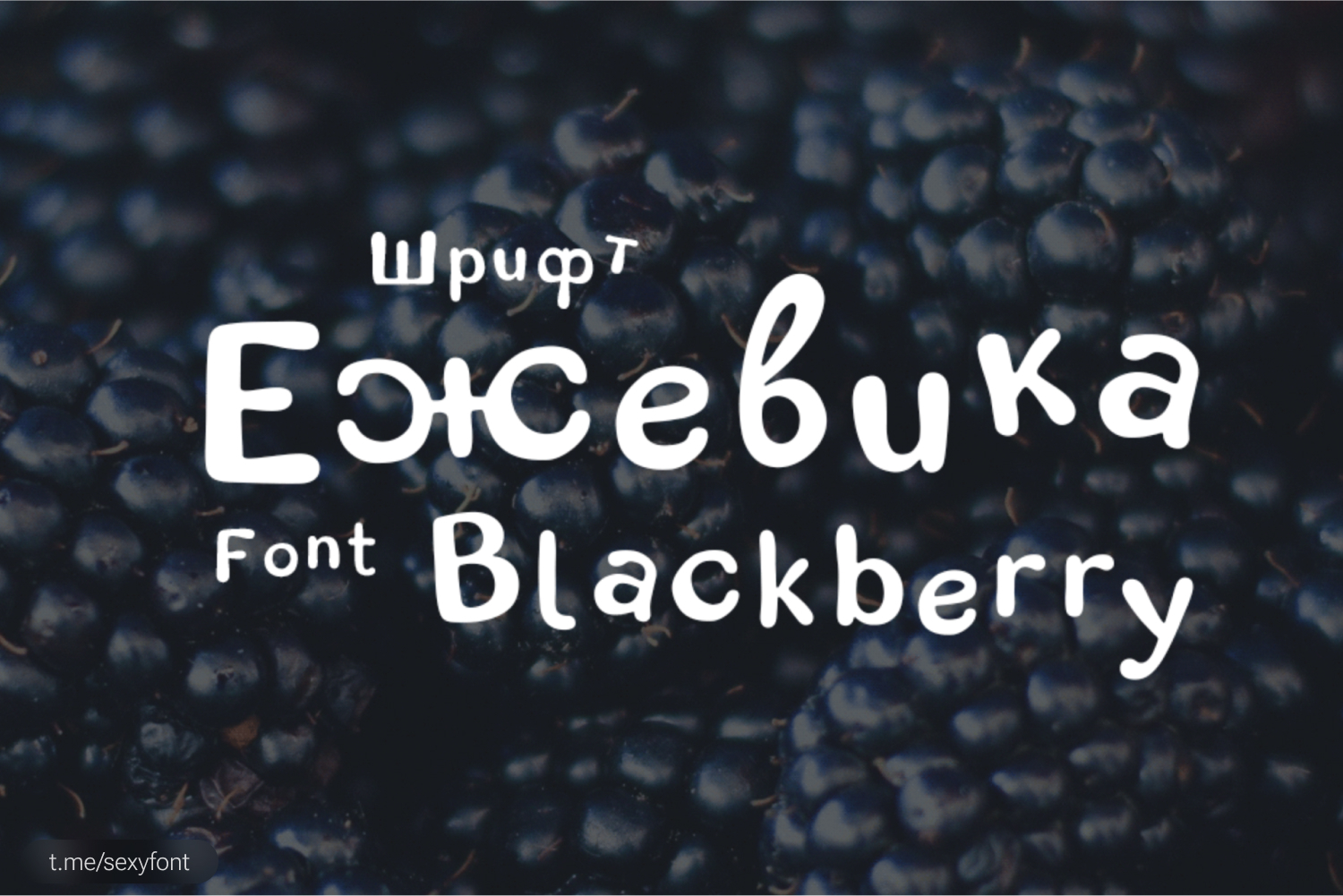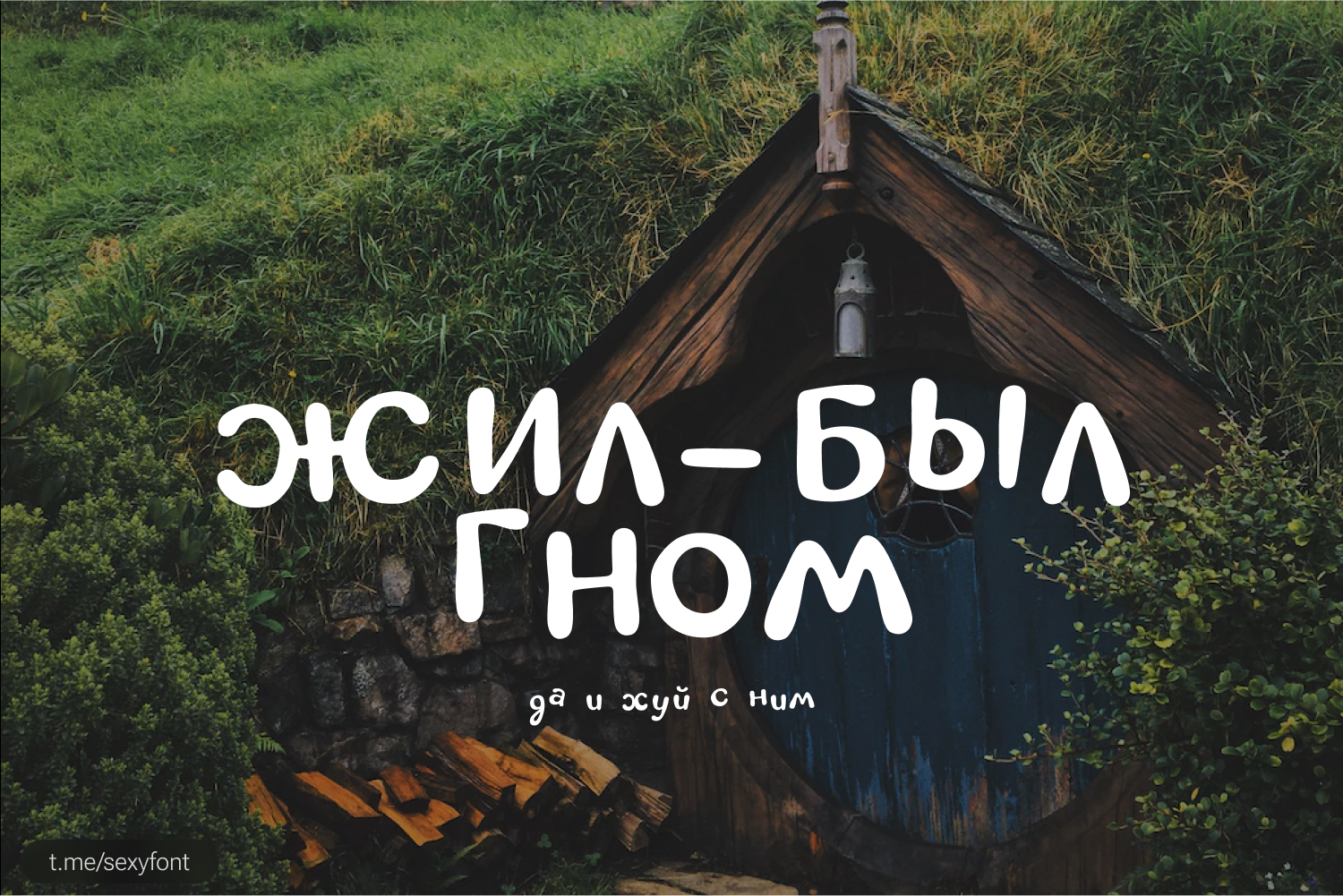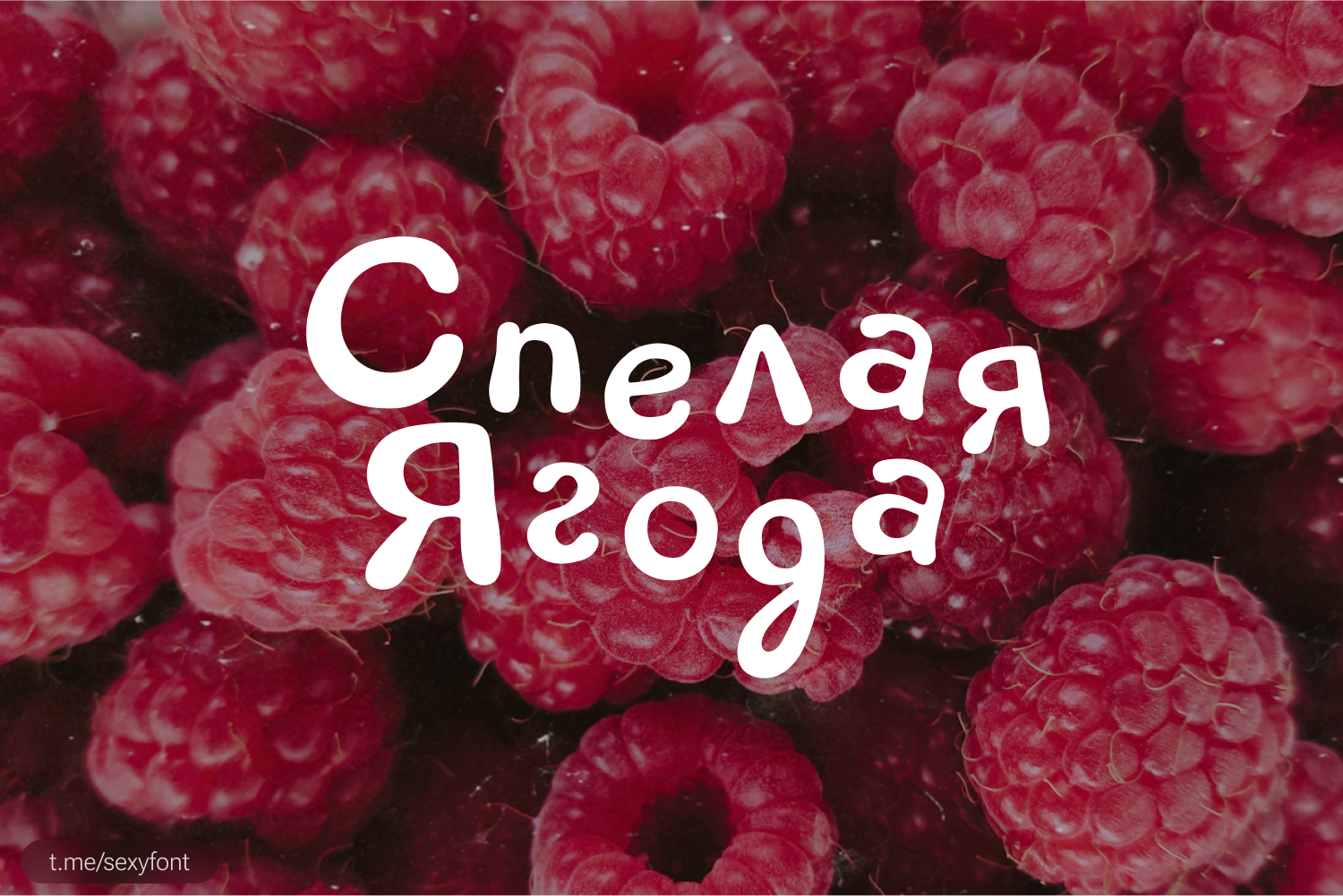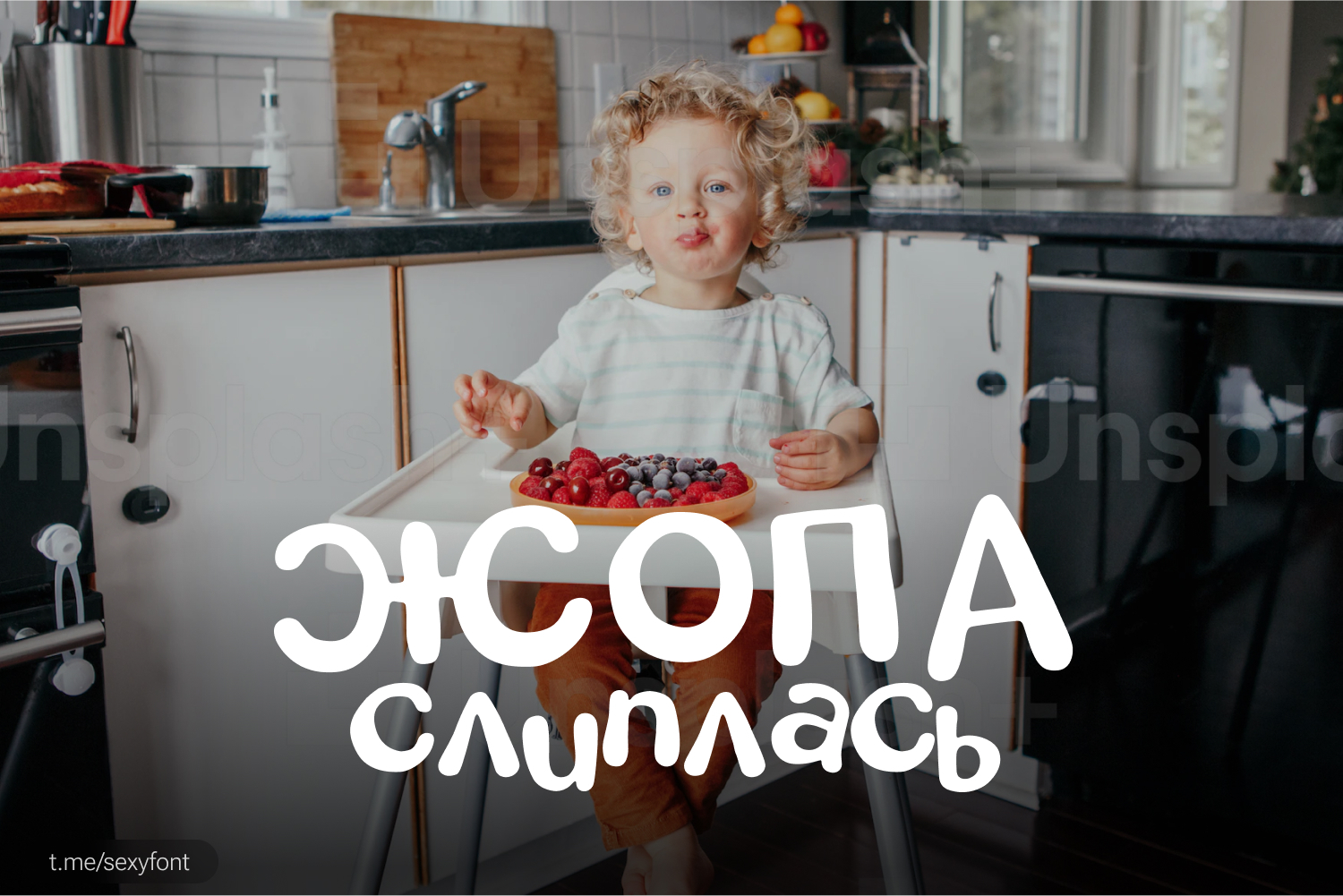
Шрифт ежевика. Бесплатная кириллица
Ежевика. Веселый и хорошо читаемый шрифт. Что еще для счастья надо? Что? Денег? Не в них счастье, когда у тебя есть такой прекрасный шрифт! ммм. Бесплатно для всего.